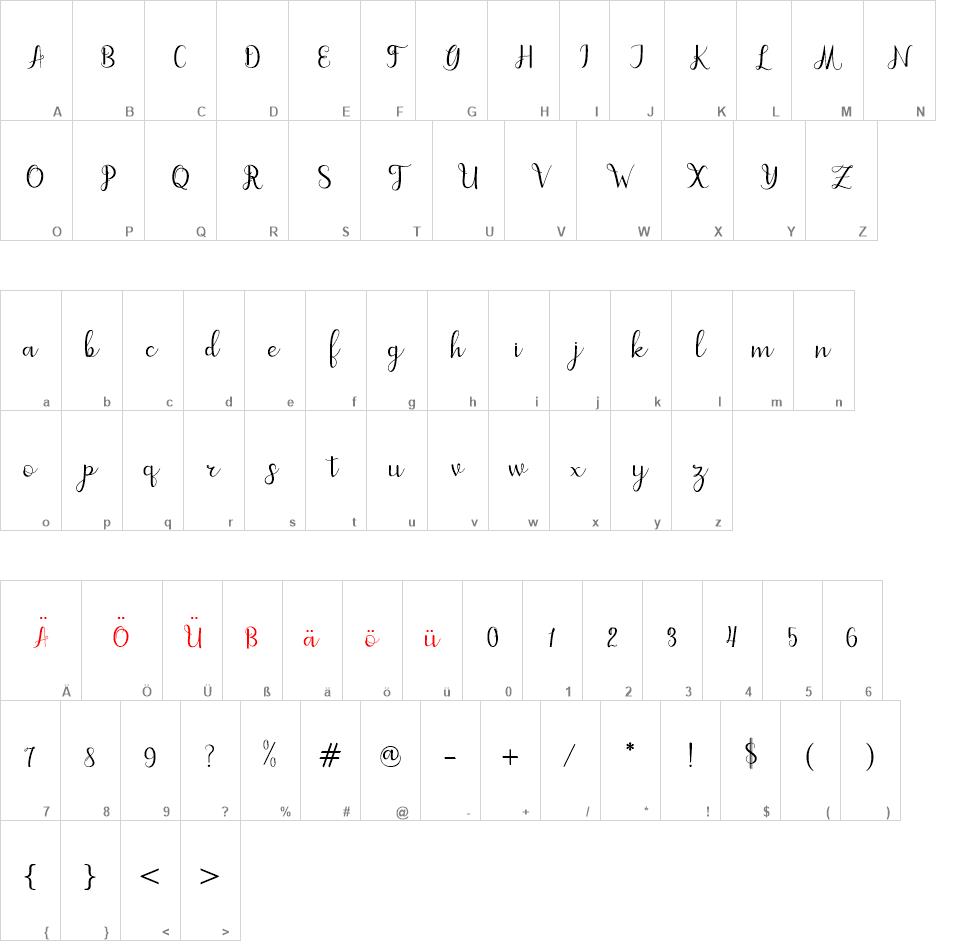
Dahlia Script
Dahlia Script font
Dahlia Script
Dahlia-Skript
eine neue, frische und moderne Schrift mit einem handgemachten Kalligrafie-Stil, dekorativen Charakteren und einer tanzenden Grundlinie! So schön auf Einladung wie Grußkarten, Branding-Materialien, Visitenkarten, Zitate, Plakate und vieles mehr !!